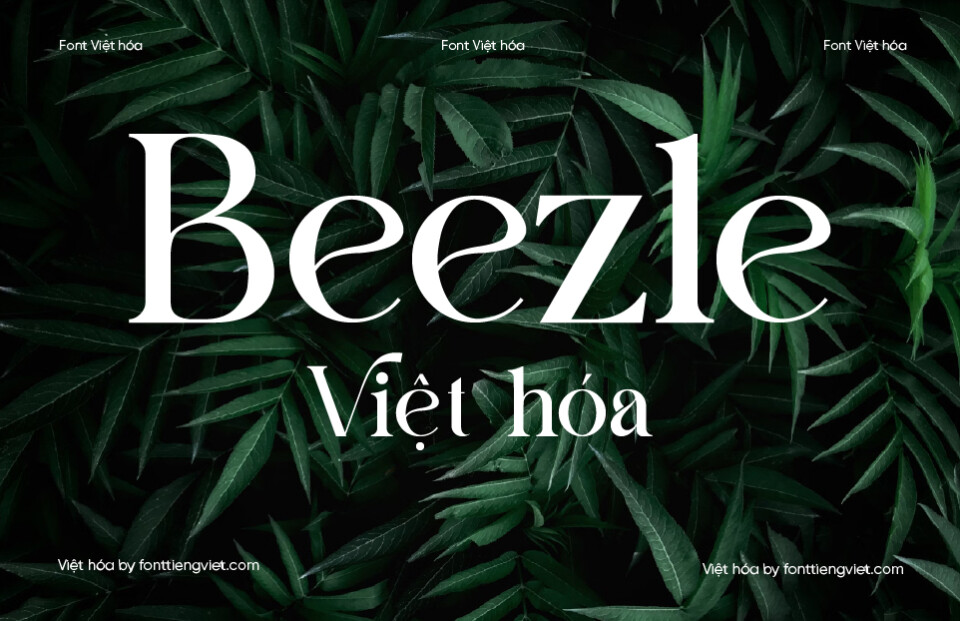
Font Việt hóa 1FTV VIP Beezle
Giới thiệu về Font Việt hóa 1FTV VIP Beezle
Trong thế giới thiết kế đồ họa hiện đại, việc lựa chọn một bộ Font Miễn Phí phù hợp đóng vai trò quyết định đến sự thành công của một tác phẩm nghệ thuật. Một trong những cái tên đang thu hút sự chú ý của cộng đồng designer chính là Font Việt hóa 1FTV VIP Beezle. Đây là một bộ phông chữ mang phong cách hiện đại, thanh lịch nhưng không kém phần phá cách, giúp các nhà sáng tạo nội dung dễ dàng truyền tải thông điệp một cách ấn tượng nhất. Việc sử dụng phiên bản Việt hóa giúp người dùng tại Việt Nam loại bỏ hoàn toàn nỗi lo về lỗi gõ dấu, tạo sự đồng bộ và thẩm mỹ tuyệt đối cho các văn bản tiếng Việt.
Đặc điểm nổi bật của Font Việt hóa 1FTV VIP Beezle
Thiết kế độc đáo và linh hoạt
Bộ Font Việt hóa 1FTV VIP Beezle sở hữu những đường nét được gọt giũa tỉ mỉ, kết hợp giữa các nét thẳng dứt khoát và các góc bo tròn mềm mại. Sự cân bằng này giúp bộ font có khả năng ứng dụng cực kỳ linh hoạt trong nhiều lĩnh vực khác nhau. Dù bạn đang thiết kế một biểu trưng sang trọng hay một tấm áp phích năng động cho các hoạt động ngoại khóa của học sinh, bộ phông chữ này đều có thể đáp ứng một cách xuất sắc. Đặc biệt, các ký tự dấu tiếng Việt đã được tinh chỉnh khoảng cách và kích thước sao cho hài hòa nhất với các chữ cái gốc, đảm bảo tính dễ đọc trên cả màn hình kỹ thuật số và các ấn phẩm in ấn vật lý truyền thống.
Phù hợp cho nhiều mục đích sử dụng
Nhờ vào tính thẩm mỹ cao, Font Việt hóa 1FTV VIP Beezle thường xuyên được các bạn trẻ ưu tiên lựa chọn cho các dự án sáng tạo cá nhân. Trong môi trường học đường, các thầy cô giáo cũng có thể sử dụng bộ font này để trang trí slide bài giảng hoặc làm tiêu đề cho các tờ báo tường, giúp bài học trở nên sinh động và lôi cuốn hơn đối với học sinh. Đối với những người làm nghề thiết kế chuyên nghiệp, đây là một lựa chọn tuyệt vời cho việc xây dựng bộ nhận diện thương hiệu, thiết kế bao bì sản phẩm hoặc tạo ra các hình ảnh truyền thông trên mạng xã hội. Khả năng hiển thị rõ nét giúp thông điệp của bạn luôn nổi bật giữa hàng nghìn thông tin khác mỗi ngày.
Lợi ích khi sử dụng Font Việt hóa 1FTV VIP Beezle trong học tập
Nâng cao tư duy thẩm mỹ cho học sinh
Việc tiếp xúc với các bộ font chữ đẹp như Font Việt hóa 1FTV VIP Beezle ngay từ khi còn ngồi trên ghế nhà trường giúp học sinh hình thành tư duy thẩm mỹ tốt hơn. Thay vì chỉ sử dụng những phông chữ hệ thống đơn điệu, việc biết cách chọn lọc và phối hợp các phông chữ nghệ thuật sẽ giúp các em tự tin hơn trong các bài thuyết trình hay các dự án nhóm. Đây cũng là bước đệm quan trọng cho những em có định hướng theo đuổi các ngành nghề liên quan đến nghệ thuật và thiết kế trong tương lai. Sự đa dạng trong kho tàng phông chữ tiếng Việt mở ra một không gian sáng tạo không giới hạn, khuyến khích sự tìm tòi và phát triển kỹ năng tin học văn phòng của thế hệ trẻ.
Kết luận về bộ Font Việt hóa 1FTV VIP Beezle